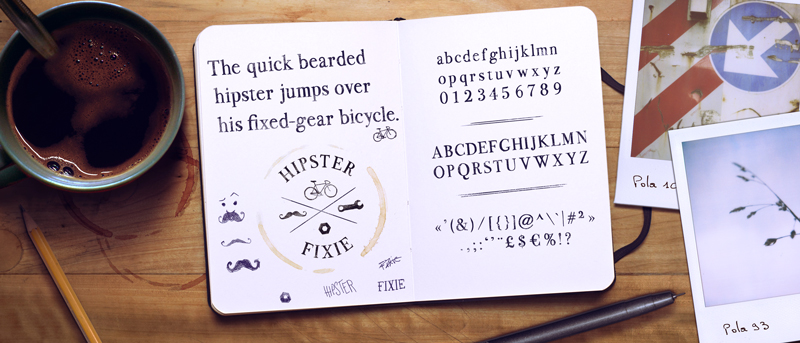
Voici une typographie à empattements avec un aspect manuel et irrégulier. Elle est inspirée de la Bodoni et contient la plupart des accents et caractères spéciaux utilisés en français et en espagnol. J'espère qu'elle vous plaira ! Et si c'est le cas, n'hésitez pas à féliciter mon travail en faisant un don via le lien situé sous le bouton de téléchargement ! Cette typo est disponible ici pour un usage personnel uniquement. Pour un usage commercial j'ai créé une version Pro, disponible ici : http://tinyurl.com/BodoFloPro Merci ! Florent ---- Here is a serif typeface with a manual and irregular appearance. It's inspired on Bodoni and contains most of the accents and special characters used in French and Spanish. I hope you enjoy it! And if you like it, don't hesitate to congratulate my work by making a donation via the link under the download button! This font is free for a personal use only. If you want to use it commercially, I created a Pro version available here : http://tinyurl.com/BodoFloPro Thanks ! Florent |